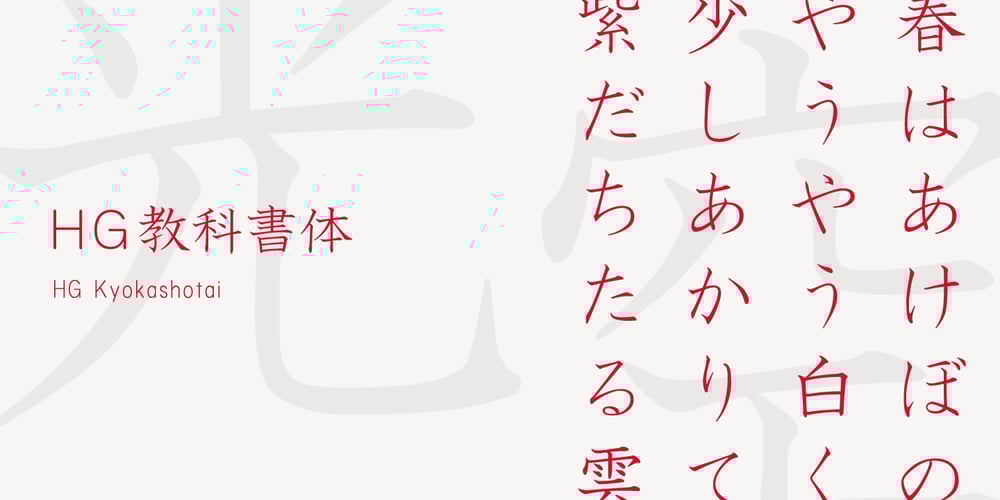
HG Kyokashotai Font Family was designed by published by RICOH. HG Kyokashotai contains 1 styles and family package options. HG教科書体は、日本活字工業の「日活教科書体」を字母とする教科書体で、児童の教科書などの使用が想定される書体です。筆で書いた文字をもとにしていますが、太さはやや細めです。伸びやかで、格調高いデザインの書体で、フォーマルな場面に合います。手書きの要素が強くコントラストも高めなので、小さいサイズでの長文に使用するよりは、それなりのサイズで、かつ、あまり長めでない文章に使用するほうがいいでしょう。